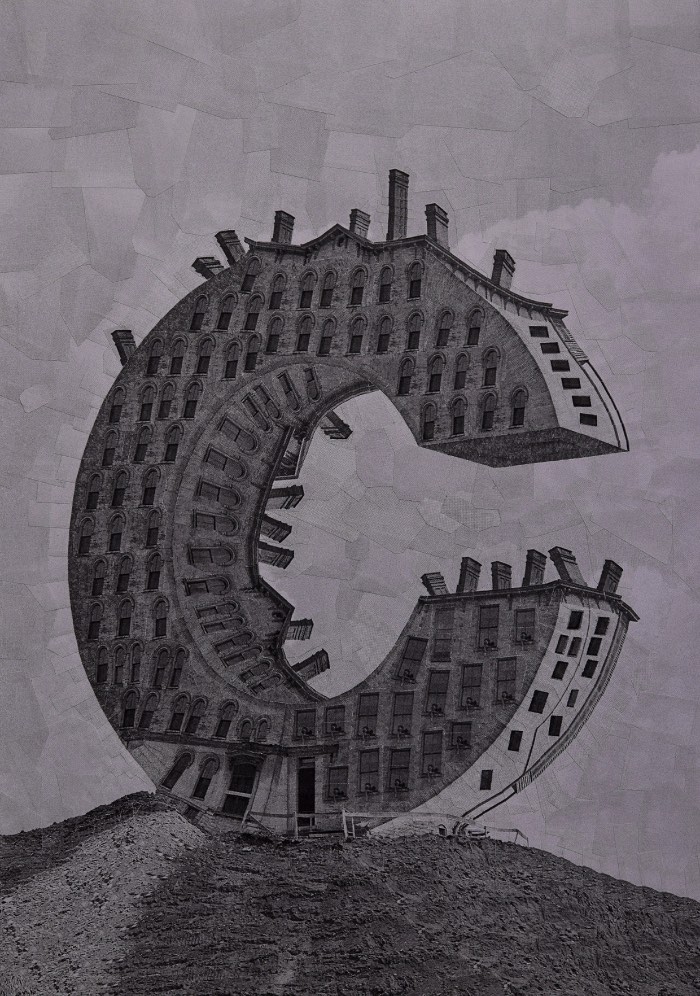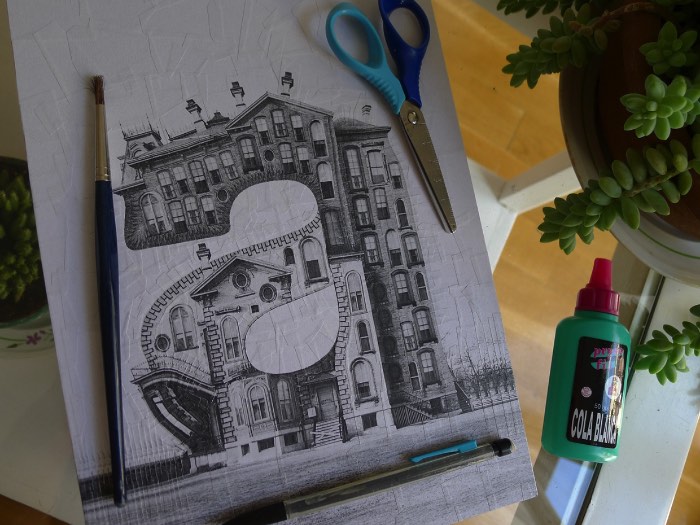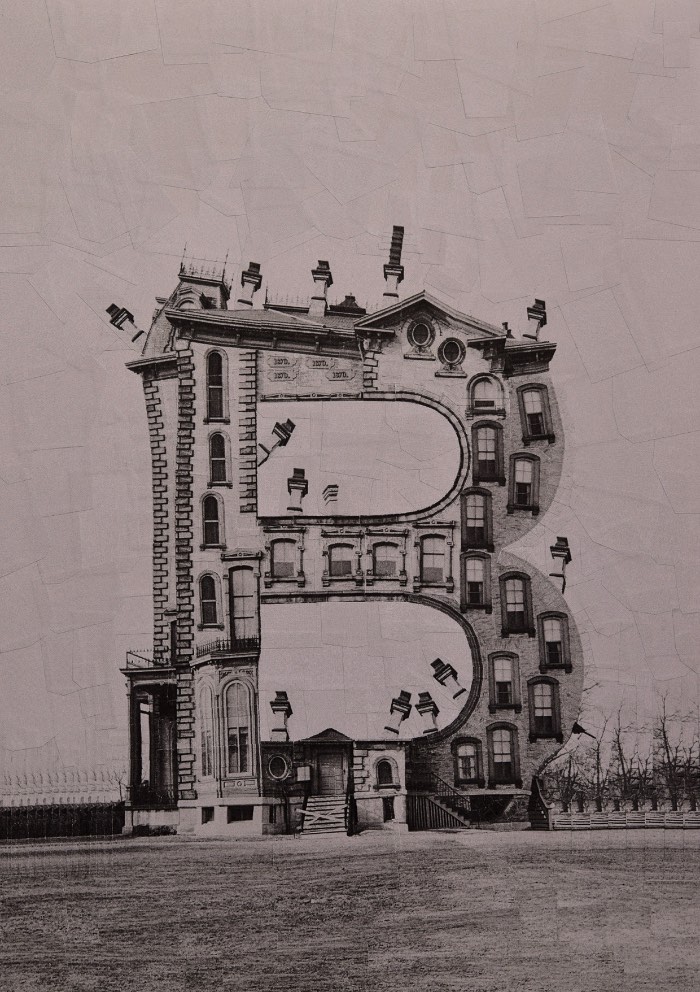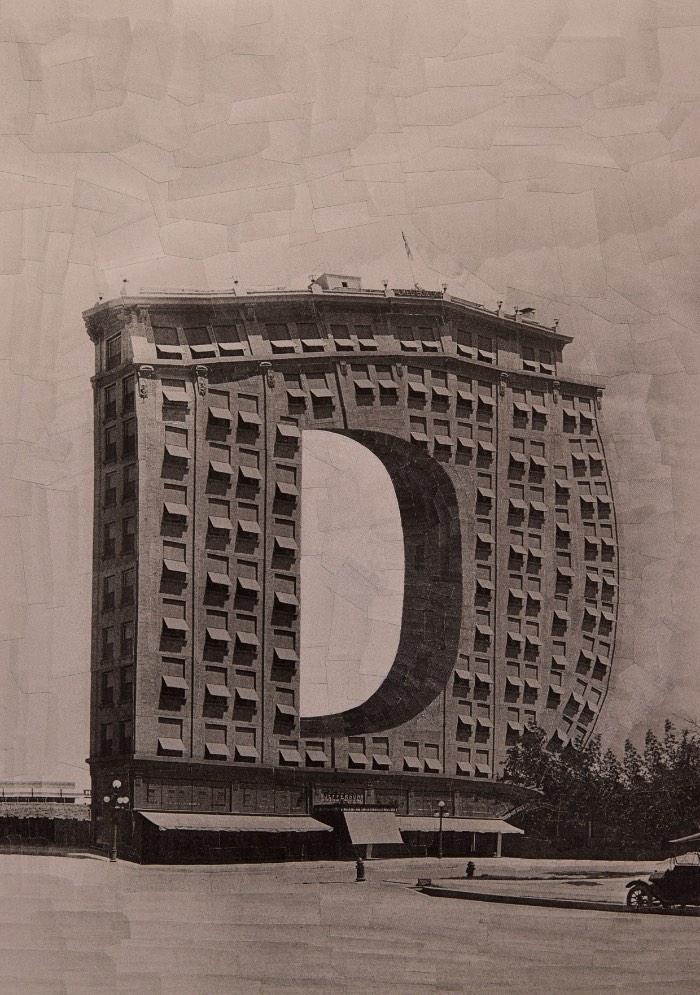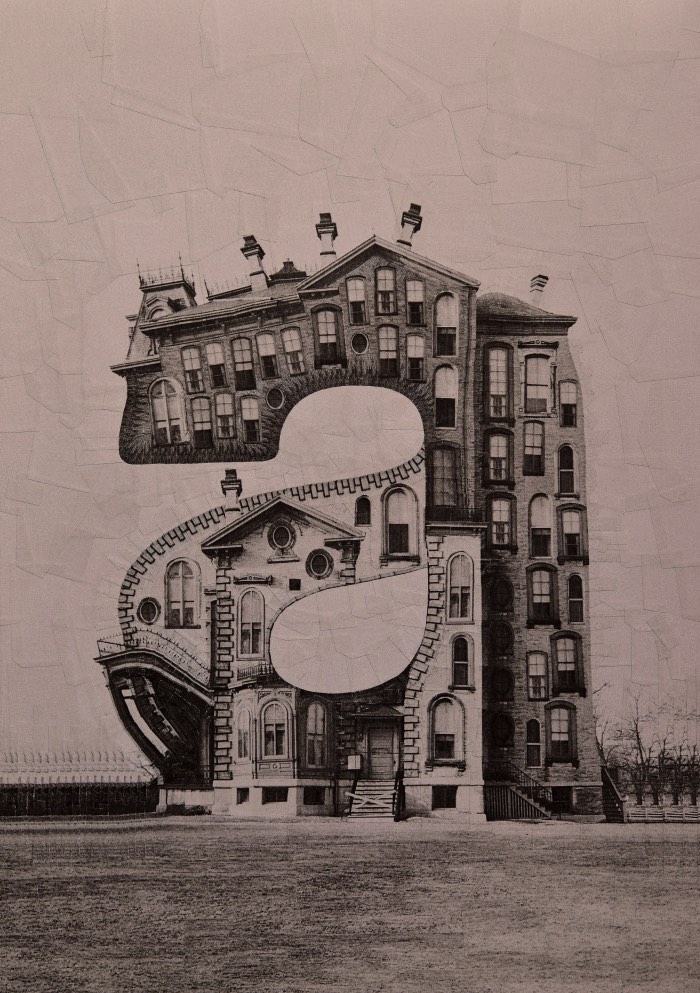
O Abecedário Colagens de Lola Dupre
Lola Dupre é uma artista espanhola com um estilo de colagem que eu acho mais do que fenomenal. O jeito com o qual ela faz caricaturas de figuras públicas de um jeito quase surreal é bem interessante e eu fiquei bem feliz quando me deparei com um projeto experimental dela. Nesse projeto ela brinca com tipografia e usa do seu estilo de colagem bem peculiar para criar uma série de imagens bem especiais.
As imagens que você vai ver logo abaixo são das primeiras letras que ela criou para seu abecedário. Temos apenas o a, b, c e d mas posso ver um estilo bem interessante e uma execução visual que clama por mais trabalhos. Só espero que ela consiga fazer mais do que essas quatro letras que temos aqui.
A personal project experimenting with typography. a B C D explores the relationships between memory and reading, the phenomena of precognitive interpretation of words and letters.
Não sei direito se esse abecedário feito com colagens de Lola Dupre vai ser algo mais do que as poucas imagens que temos aqui. Eu realmente gostaria de ver um alfabeto inteiro mas imagino que isso seria muito trabalho para uma experimentação. Mas posso ter esperanças aqui né?